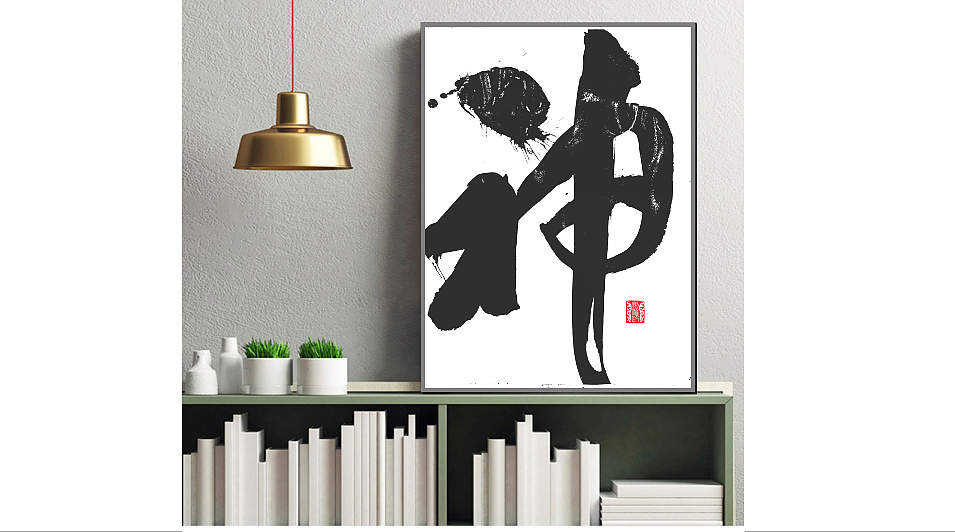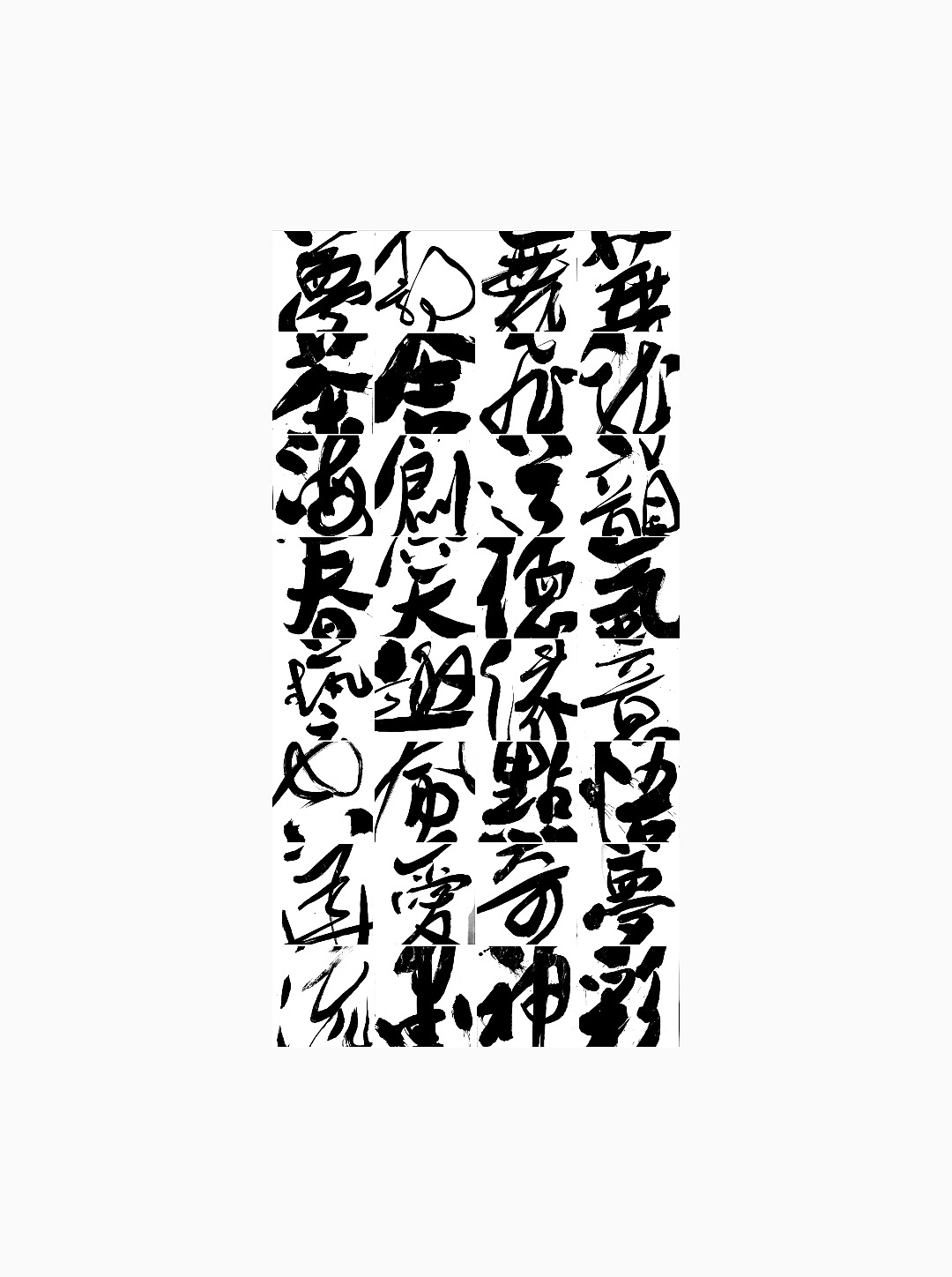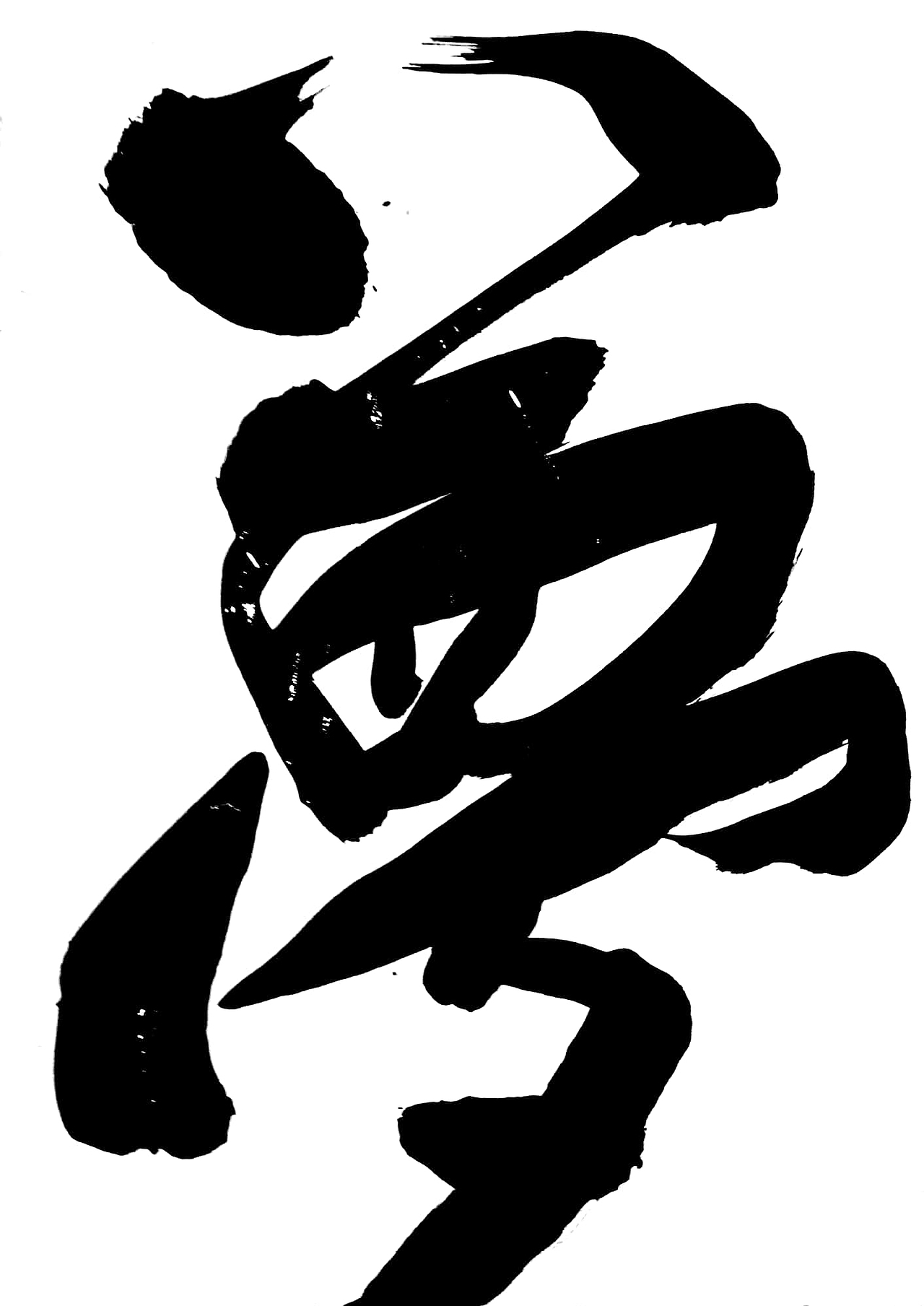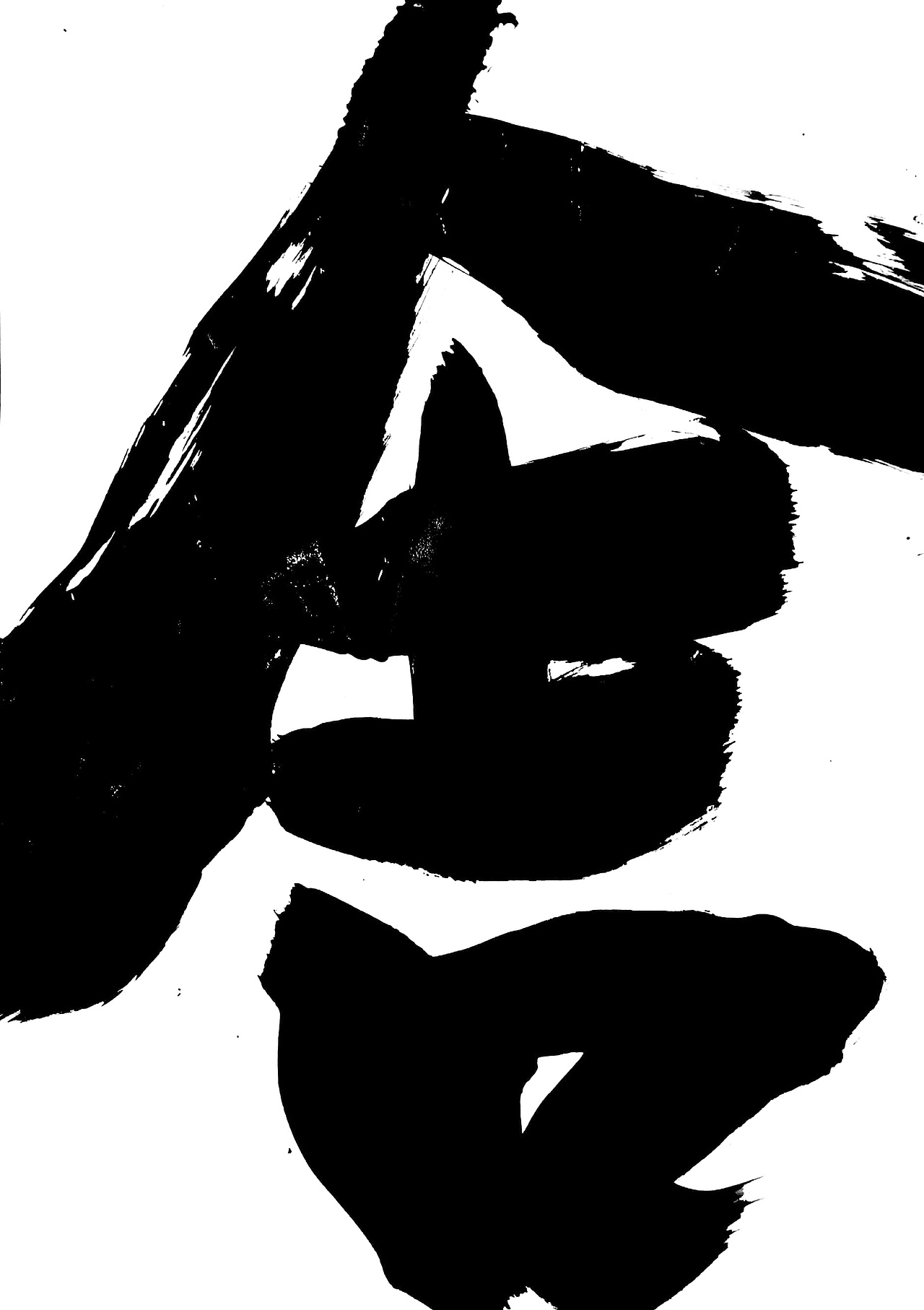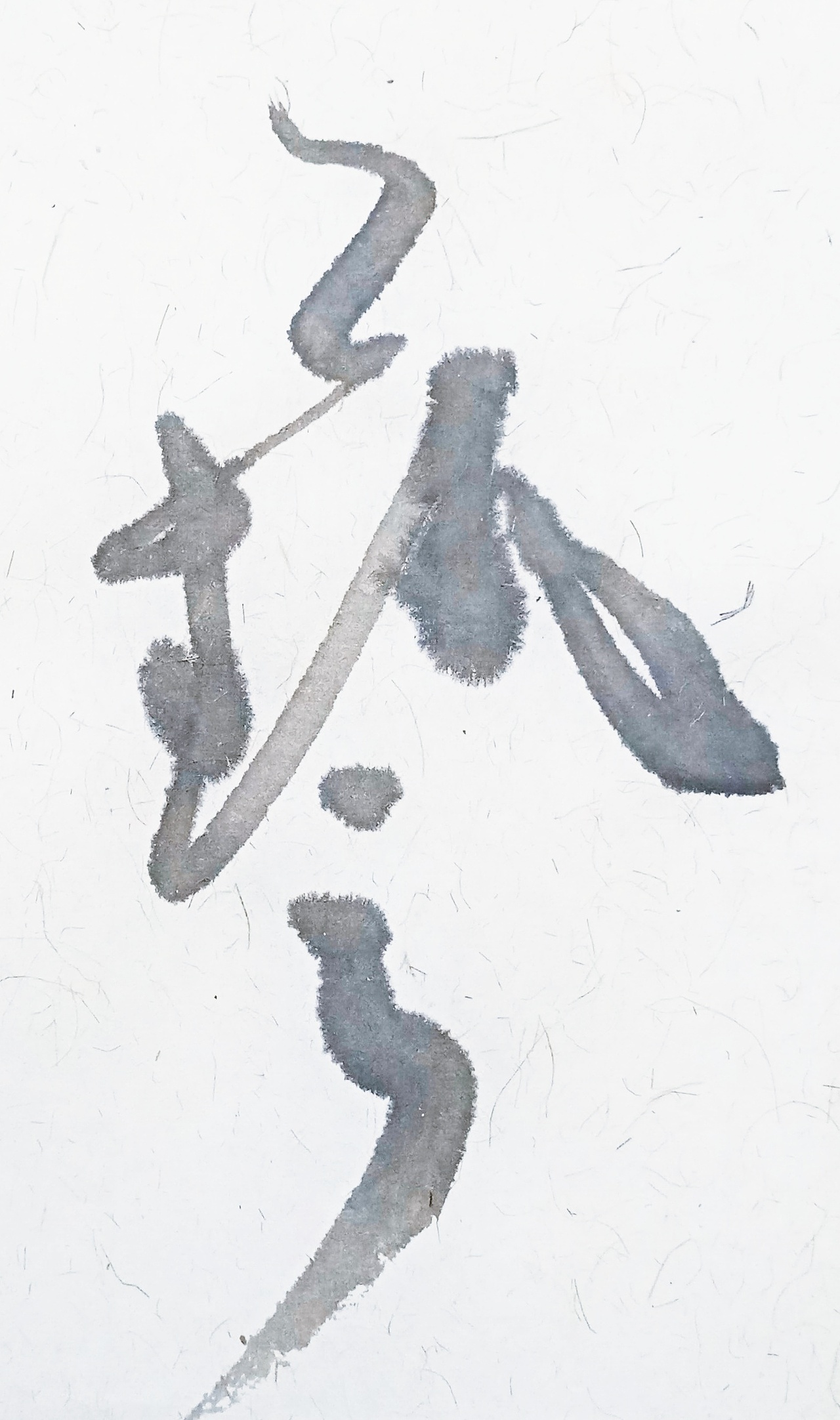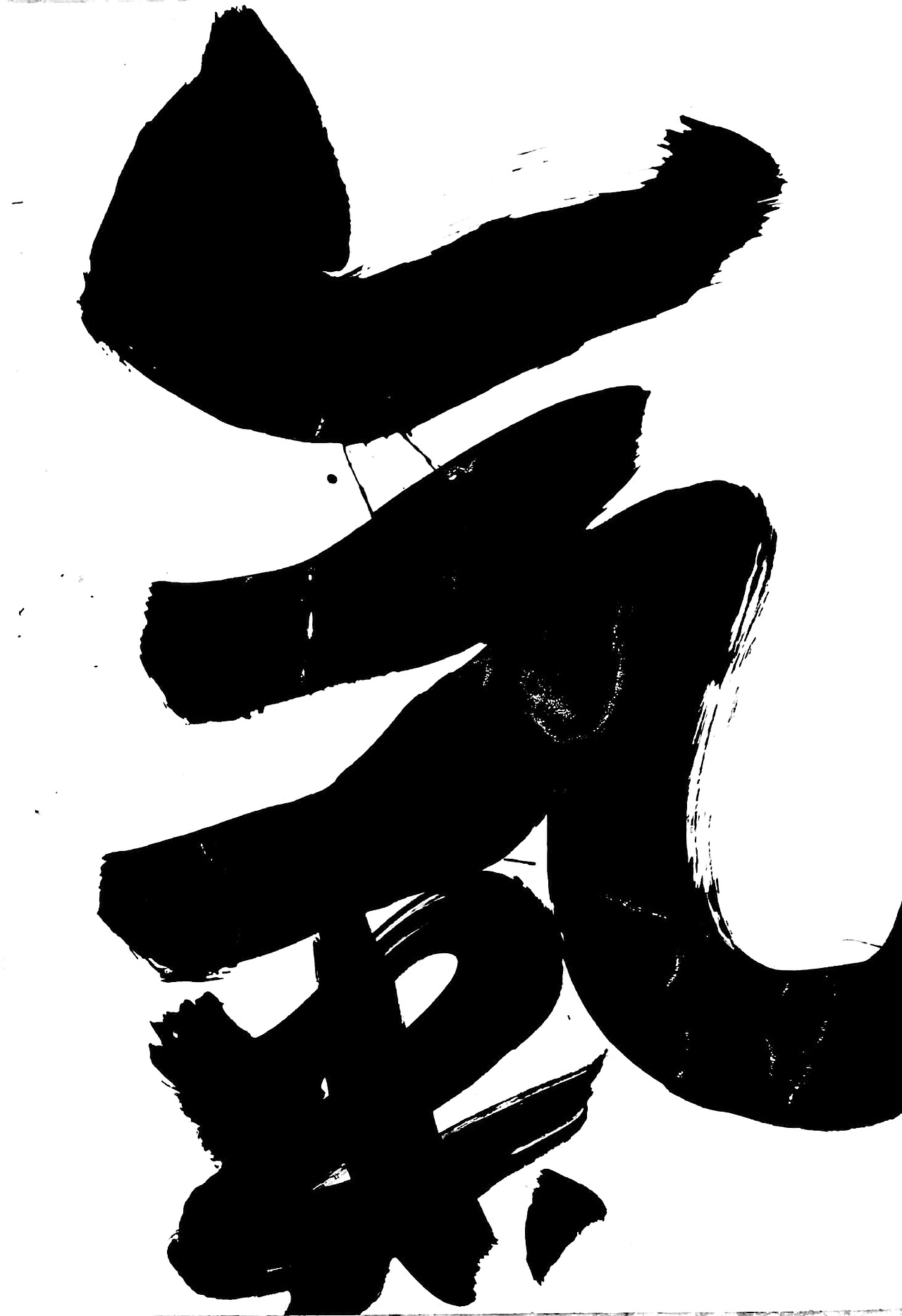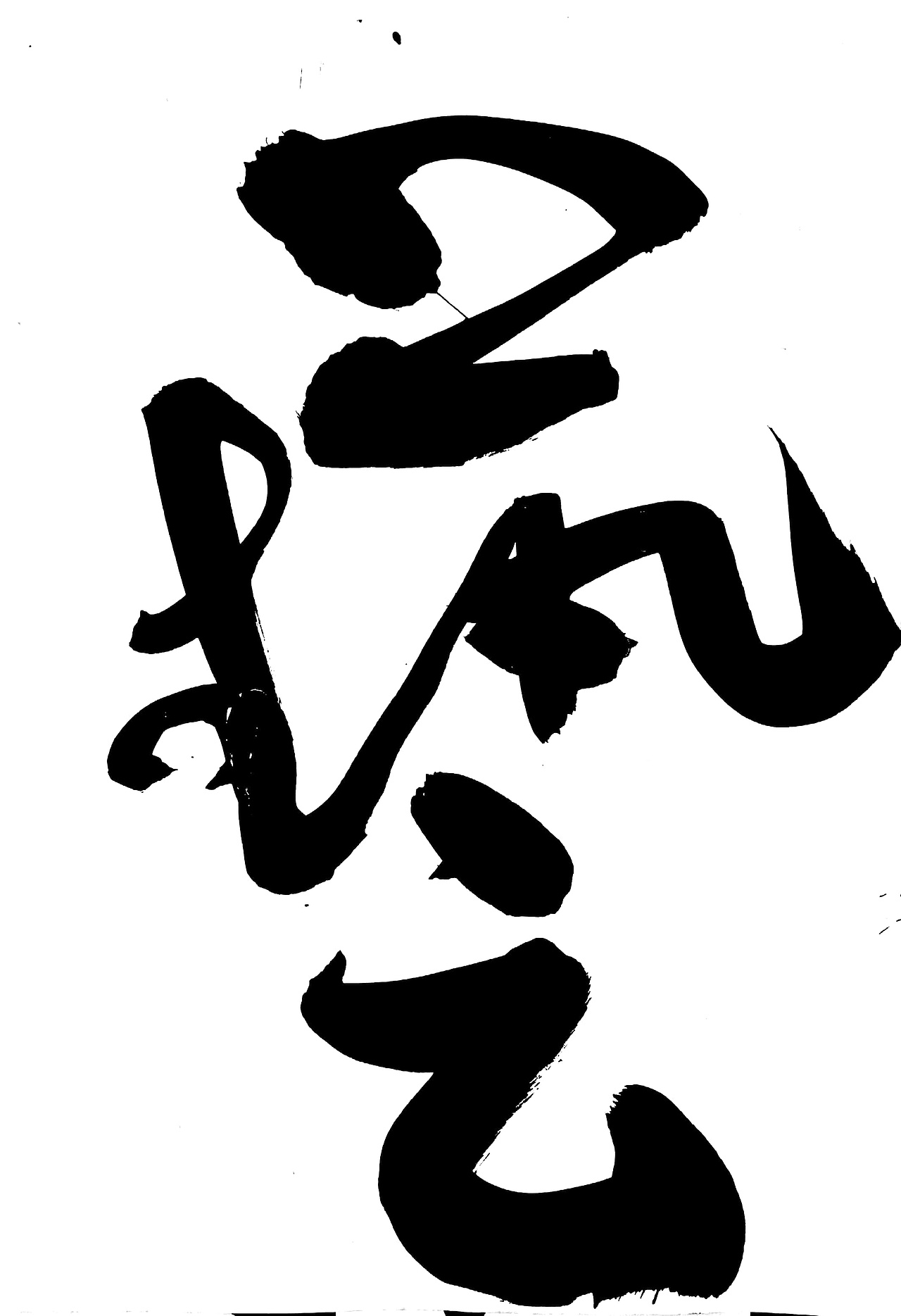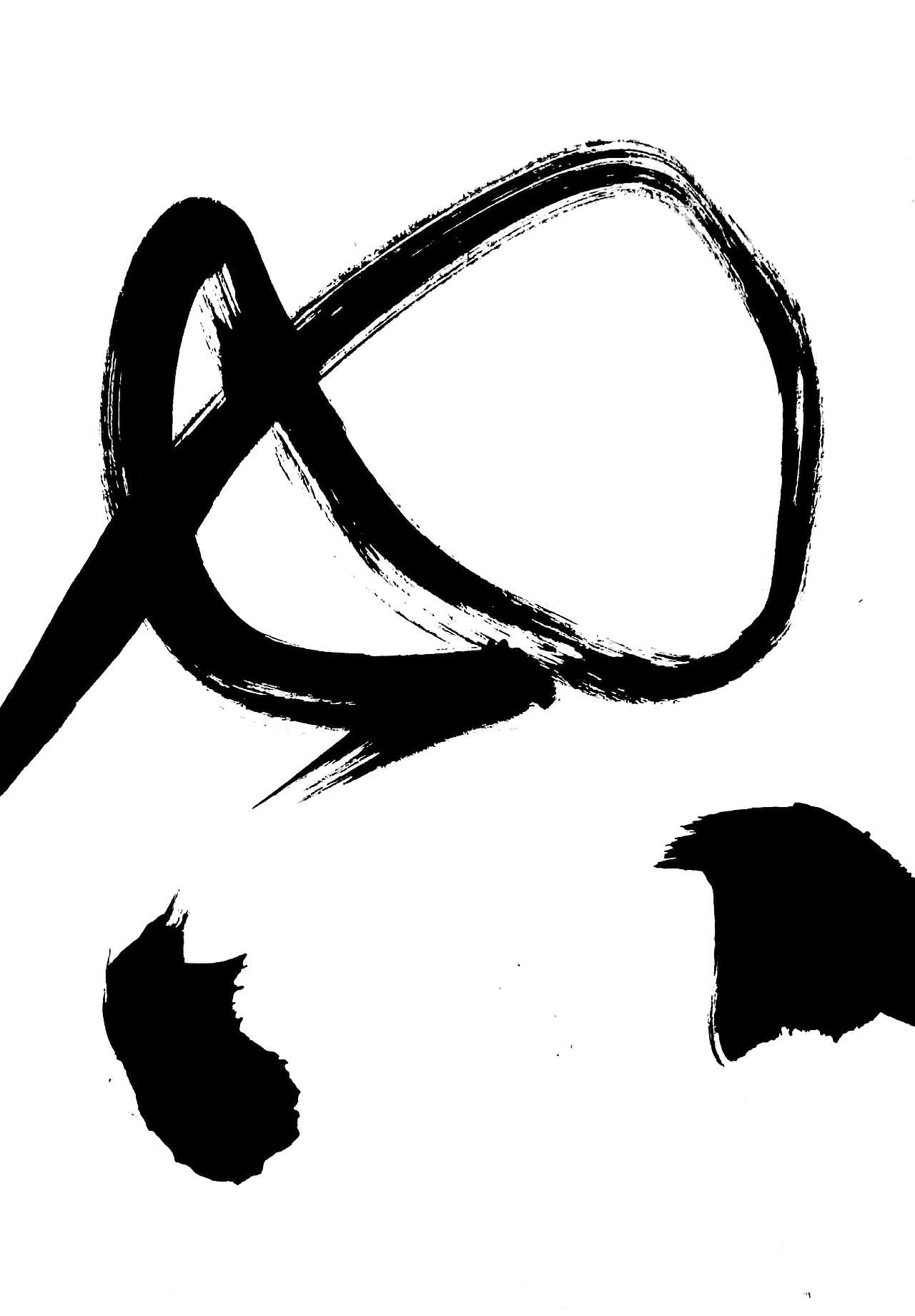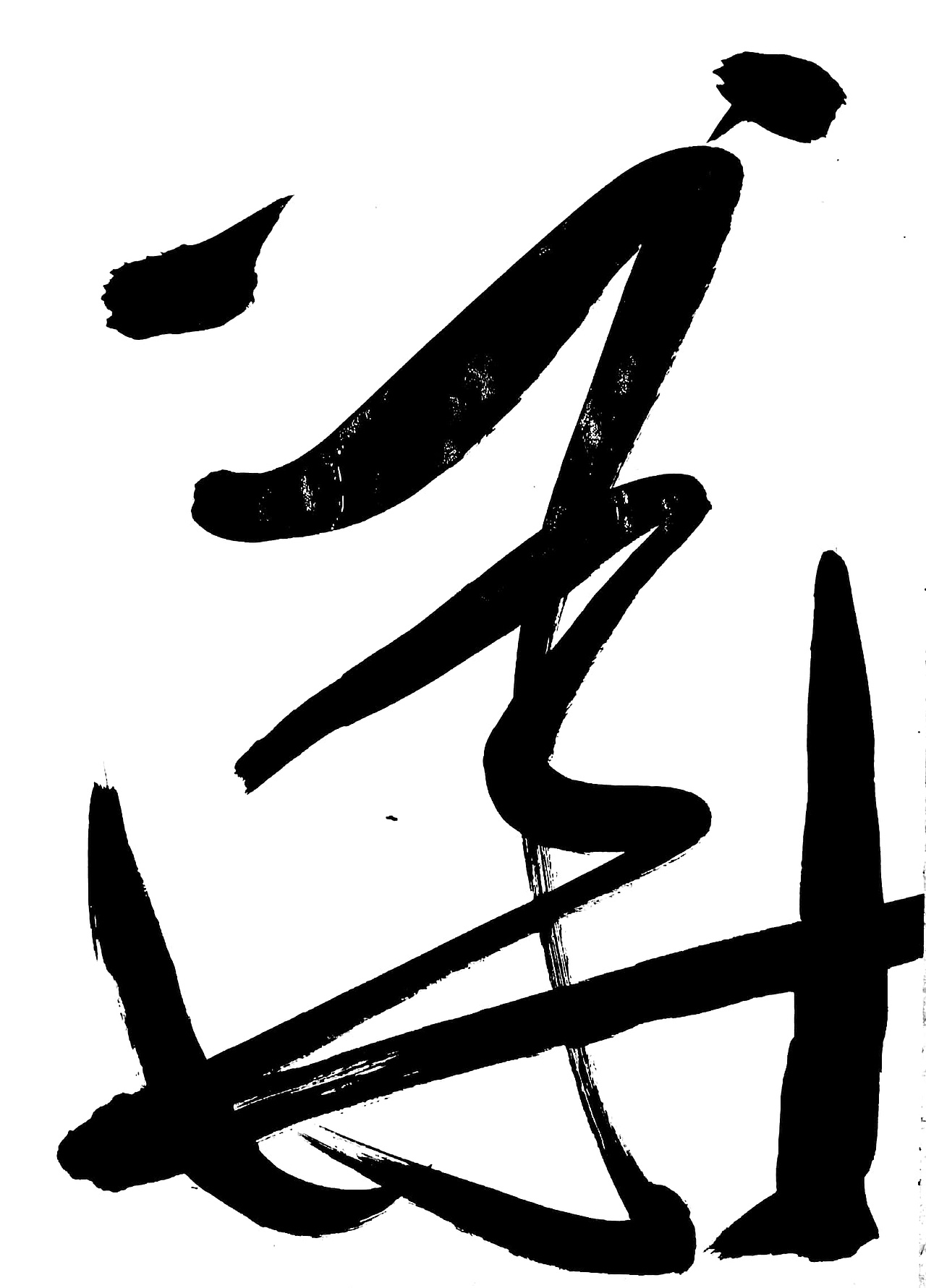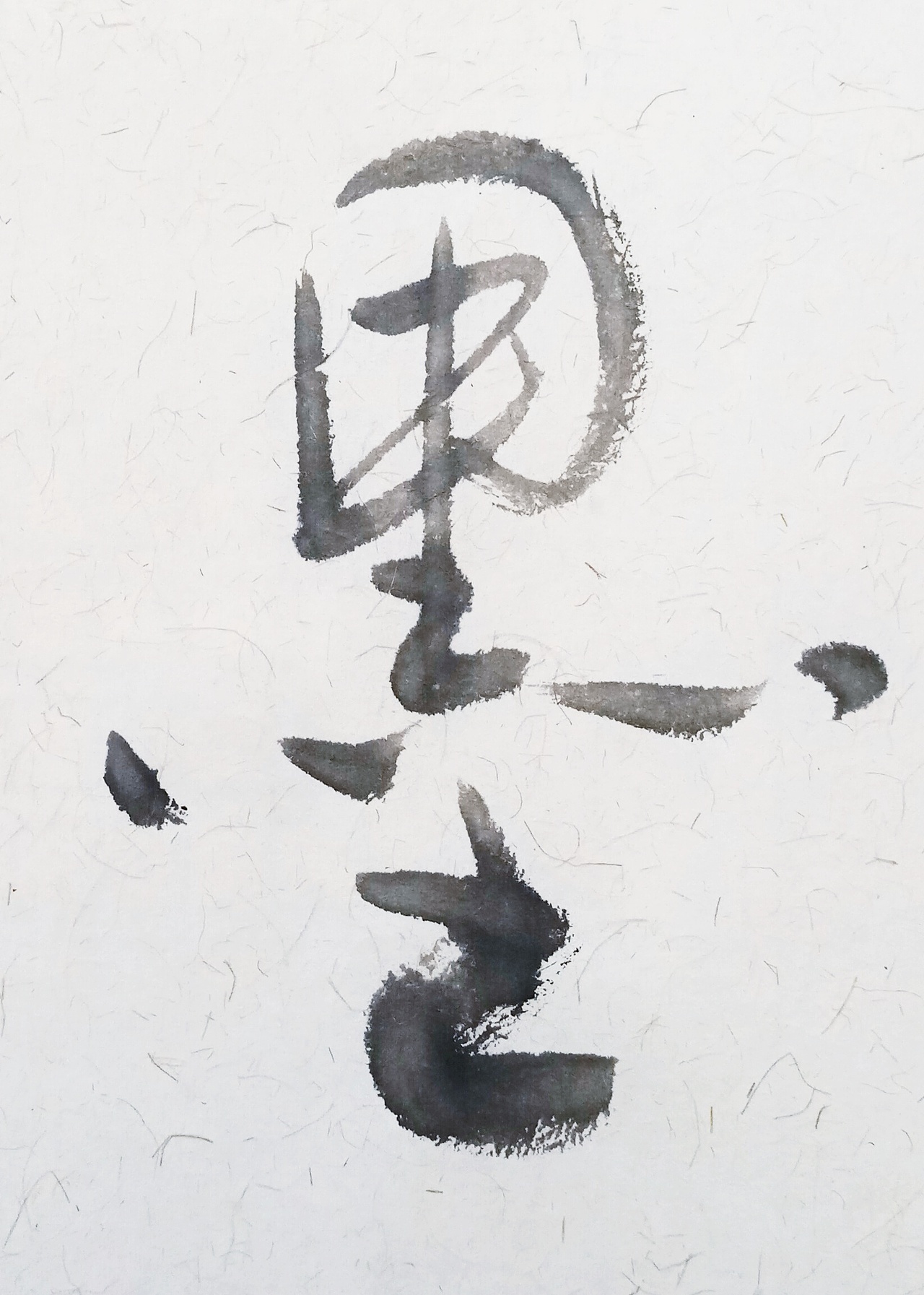
在没有电脑特效的年代,
我们常常可以从中国香港、台湾、澳门的大街上看到手写的店招(招牌)。
在那个年代,人们购物交易认准的就是这一块块金字招牌,所谓一字千金,掷地有声。
这是一种文化自信,商业诚信,更是人情味的体现。
每一块招牌字体的背后,或许都有一段耳熟能详的故事。
每一块手写店招,它时刻提醒着你这是哪里,这里生活着怎样一群人,他们的生活是什么模样。
所谓,手写体文字带有掌心的温度,温暖人心,生生不息。
手写体店招,塑造了一个品牌的鲜明个性;
手写体店招,是一座城市独特的文化符号;
手写体店招,蕴藏了店家正道不欺经营哲学。
手作精磨,守正创新。
每一块城市的店招,都在为这个时代写诗。
(1)印象深刻:手写的文字,带有掌心的温度,让您有种身临其境的感觉,亲切而自然,时尚又彰显个性。与传统几何logo或者字库字体相比较,手写体的文字标志,给人留下的印象会更加深刻。
(4)体现文字的造型美和艺术性:无论是中文、英文还是哪个国家的文字,通过设计师的再创造,融入设计师的别具匠心,辅以平面构图的美学原则,让文字焕发新的活力与生机。